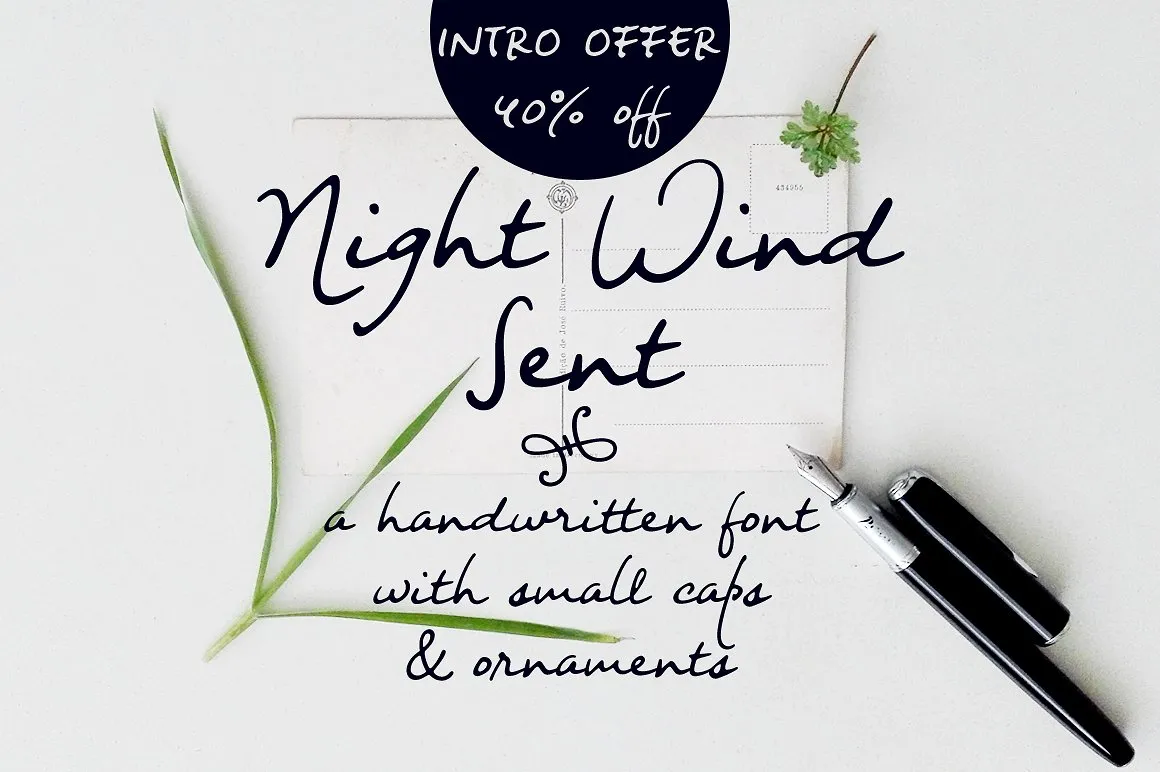
Night Wind Sent Sample Font – Download Grátis
A Night Wind Sent é uma elegante fonte escrita à mão que oferece um toque suave e sofisticado aos seus projetos. Esta demo versão gratuita para uso privado foi criada por Justlikethistrain, designer talentoso conhecido pela sua habilidade em criar fontes que se encaixam perfeitamente em diversos estilos de design. Em sua forma completa, a Night Wind Sent inclui uma rica variedade de caracteres, garantindo uma experiência visual única e profissional para os seus projetos digitais. Com suas trações elegantes e harmoniosas, Night Wind Sent é ideal para trabalhos que exigem um toque delicado e único. É perfeito para criar design gráfico sofisticado, identidades corporativas ou até mesmo anúncios, garantindo sempre uma presença visual impecável. Este é o tipo de fonte escrita à mão que você precisa se deseja incorporar um elemento autêntico e suave em seus projetos digitais.